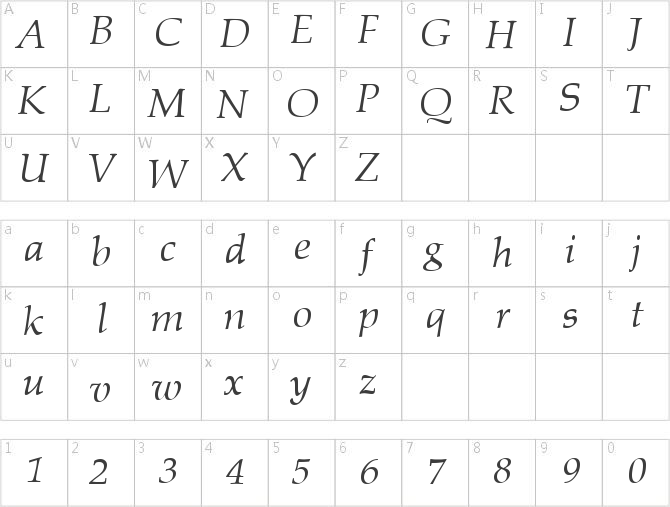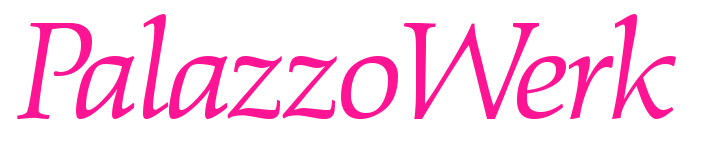
字體名稱: Palazzo
PalazzoWerk
PalazzoWerk字體字庫(kù)是一款讓人賞心悅目、百看不厭的英文字體,適合各類廣告和產(chǎn)品包裝設(shè)計(jì)應(yīng)用,字體大小0.06MB,格式為ttf字體,上傳用戶是昊天金誠(chéng),作者/版權(quán)方為未知